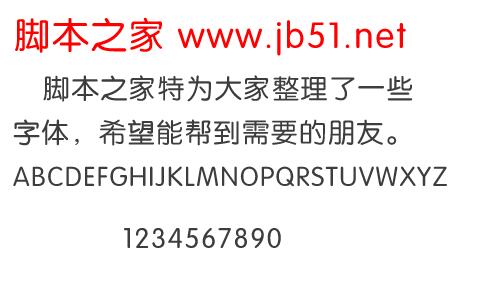
迷你準(zhǔn)圓字體是一款的較有特色的中文字體,該字體字型圓潤飽滿,端正大方得體,筆法舒展柔和,整體效果非常出眾,字里行間也充滿了趣味性,可以很好的應(yīng)用于文本裝潢、信息展示、網(wǎng)頁設(shè)計(jì)、篆刻制模、數(shù)據(jù)制作、裝潢設(shè)計(jì)、計(jì)算藝術(shù)設(shè)計(jì)、視覺設(shè)計(jì)、字帖等一切合法應(yīng)用場景,有喜歡的朋友可免費(fèi)下載收藏。